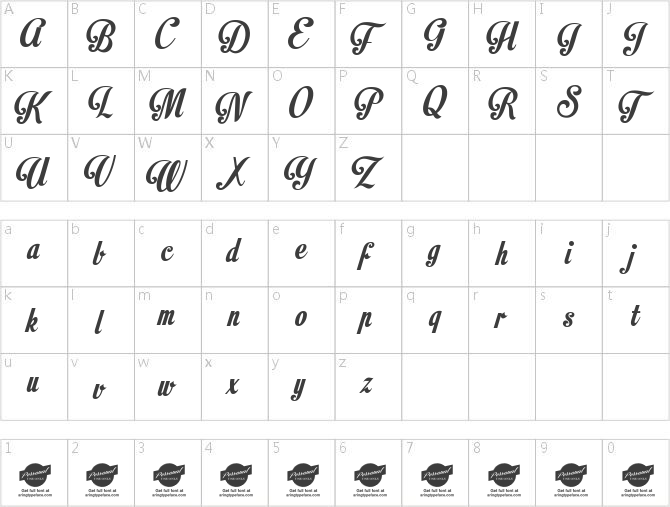
MotionPicture_PersonalUseOnly
MotionPicture_PersonalUseOnly介绍
MotionPicture_PersonalUseOnly字体字库是一款让人赏心悦目、百看不厌的英文字体,适合各类广告和产品包装设计应用,字体大小0.25MB,格式为ttf字体,上传用户是welking,作者/版权方为未知